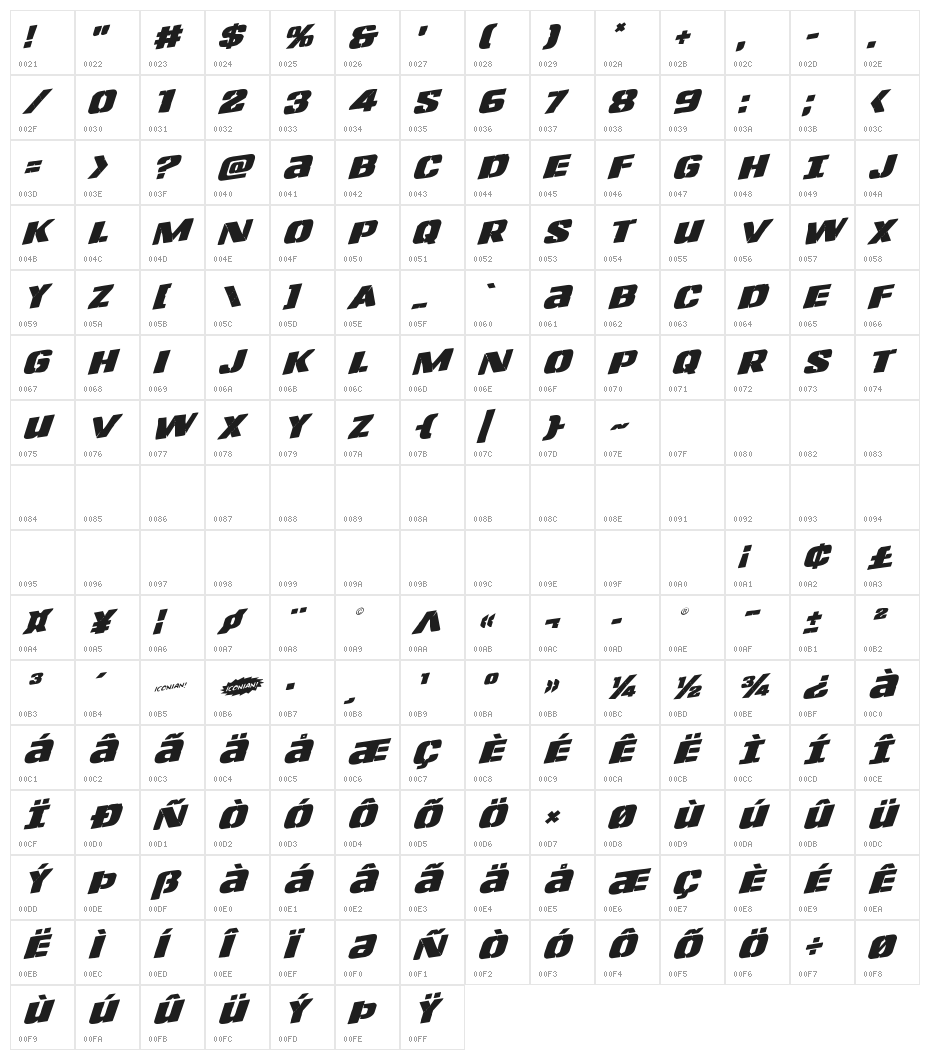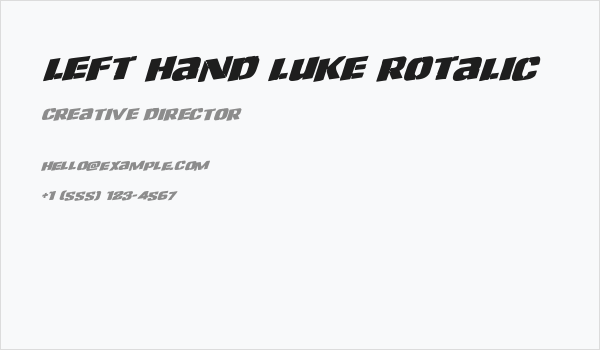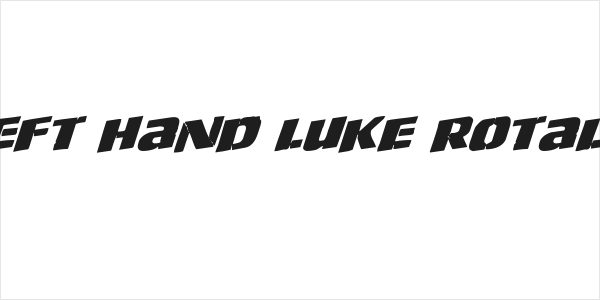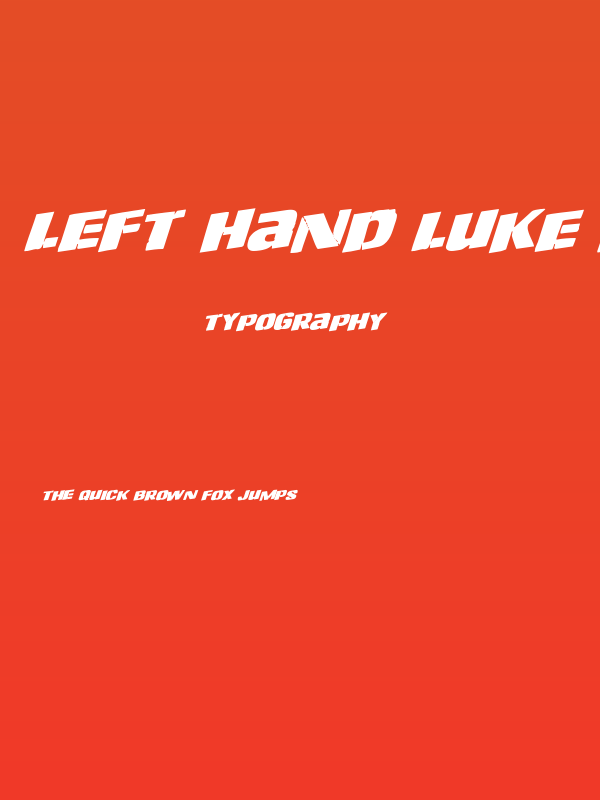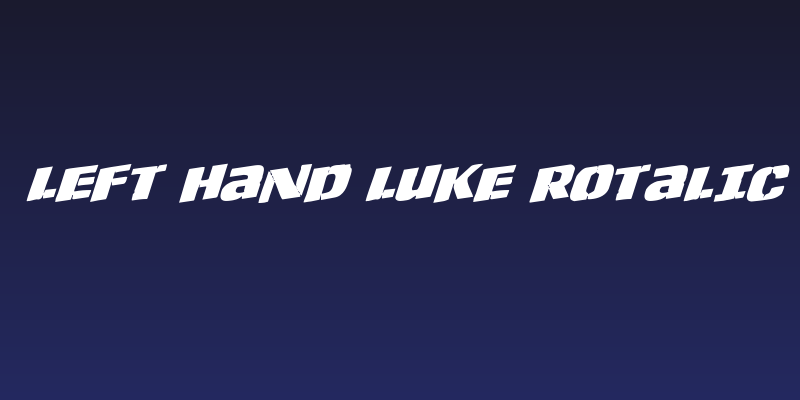
Left Hand Luke Rotalic Font
✎ Distorted Eroded
| Vorgeschlagene Projekte | Ideal for sports branding, action-themed posters, dynamic logos, and eye-catching headlines. |